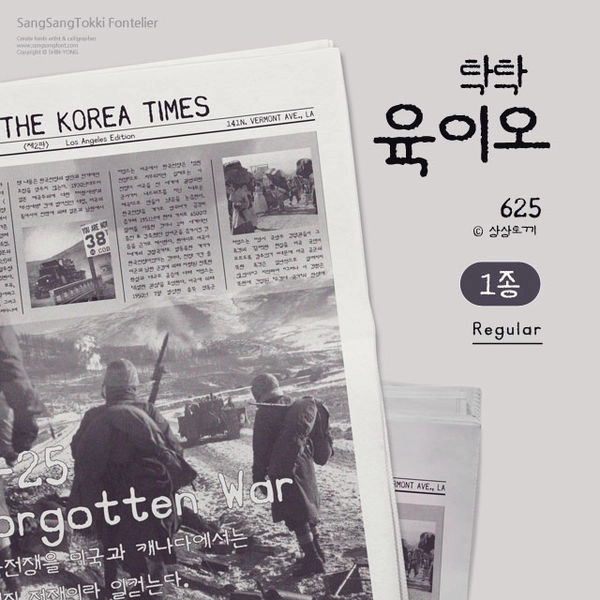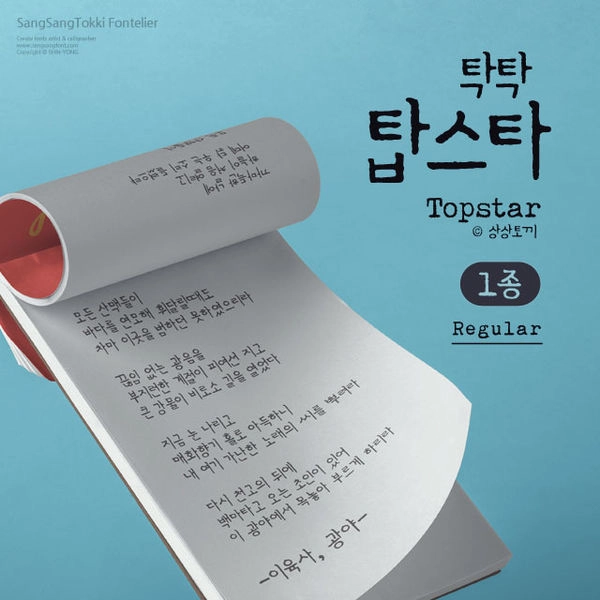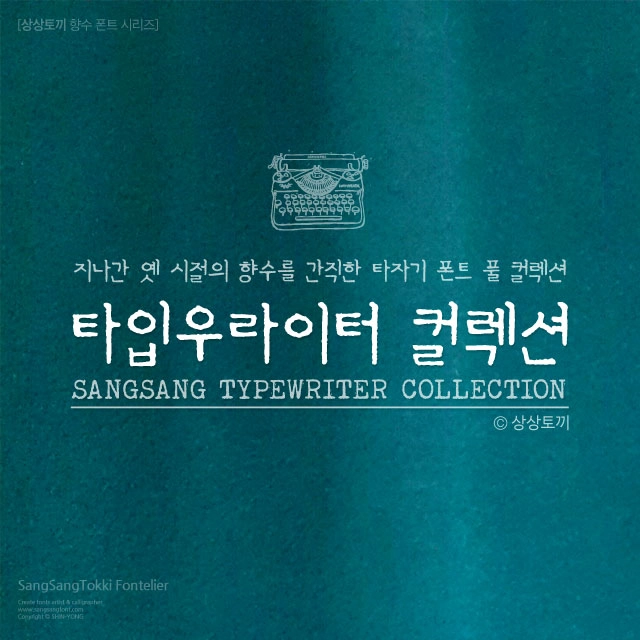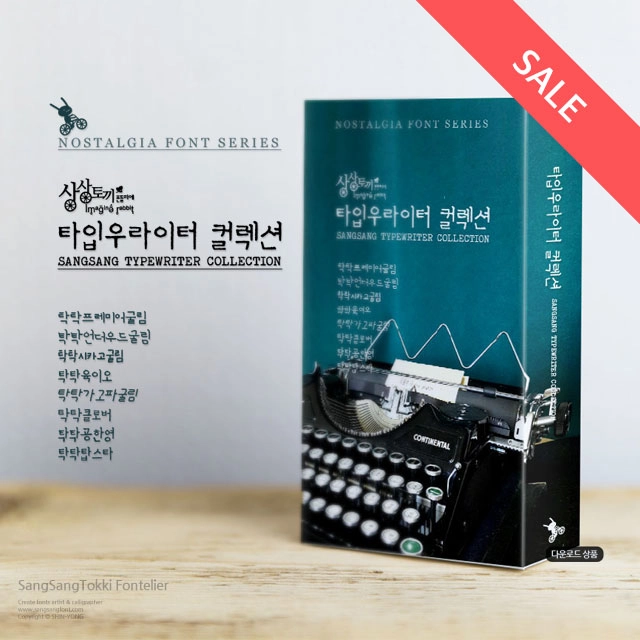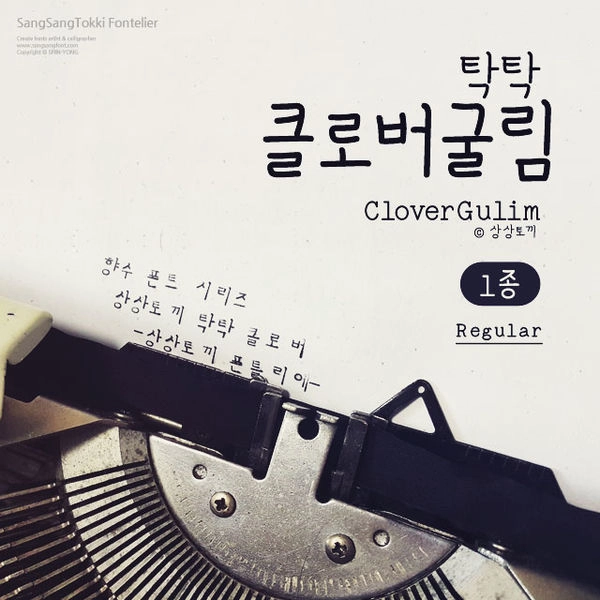
타입우라이터 컬렉션 8종
지나간 옛 시절의 향수를 간직한 타자기 폰트 풀 컬렉션, 타입우라이터 컬렉션 8종
탁탁프레미어굴림 Regular 1종
탁탁언더우드굴림 Regular 1종
탁탁시카고굴림 Regular 1종
탁탁육이오 Regular 1종
탁탁가고파굴림 Regular 1종
탁탁클로버 Regular 1종
탁탁공한영 Regular 1종
탁탁탑스타 Regular 1종